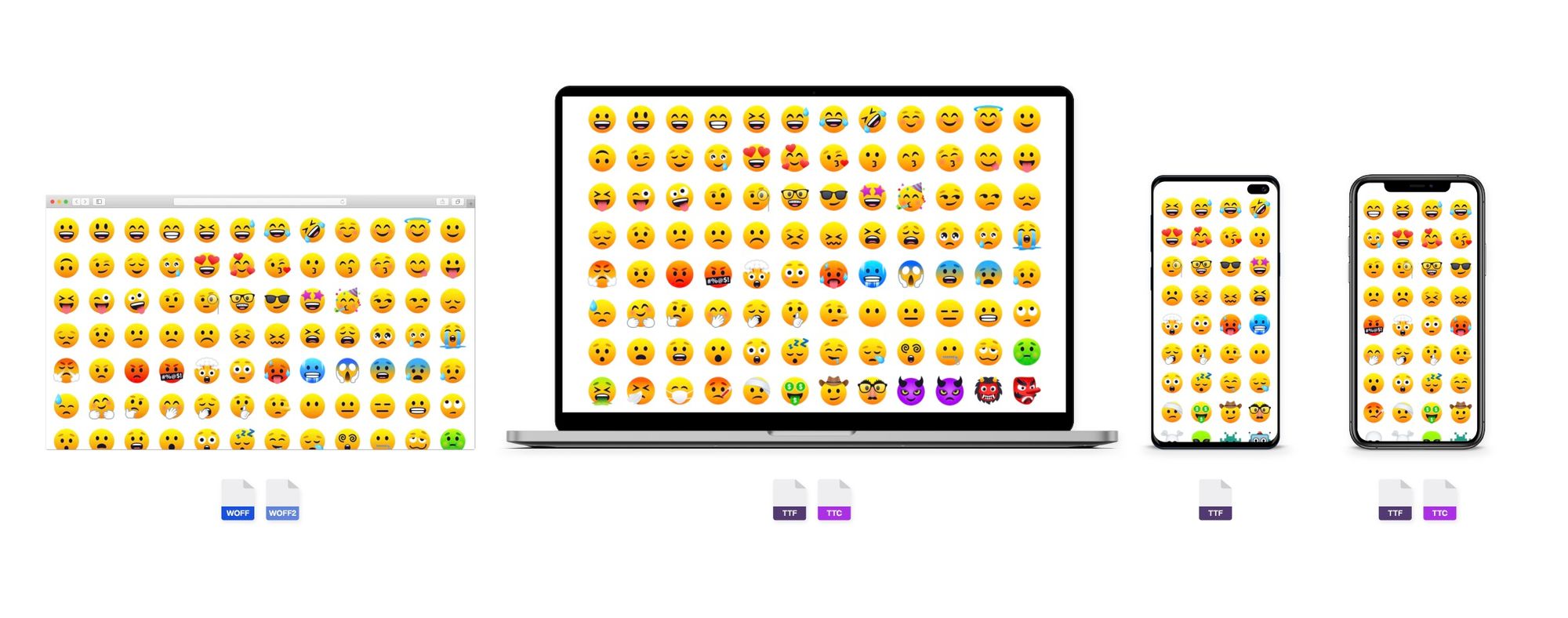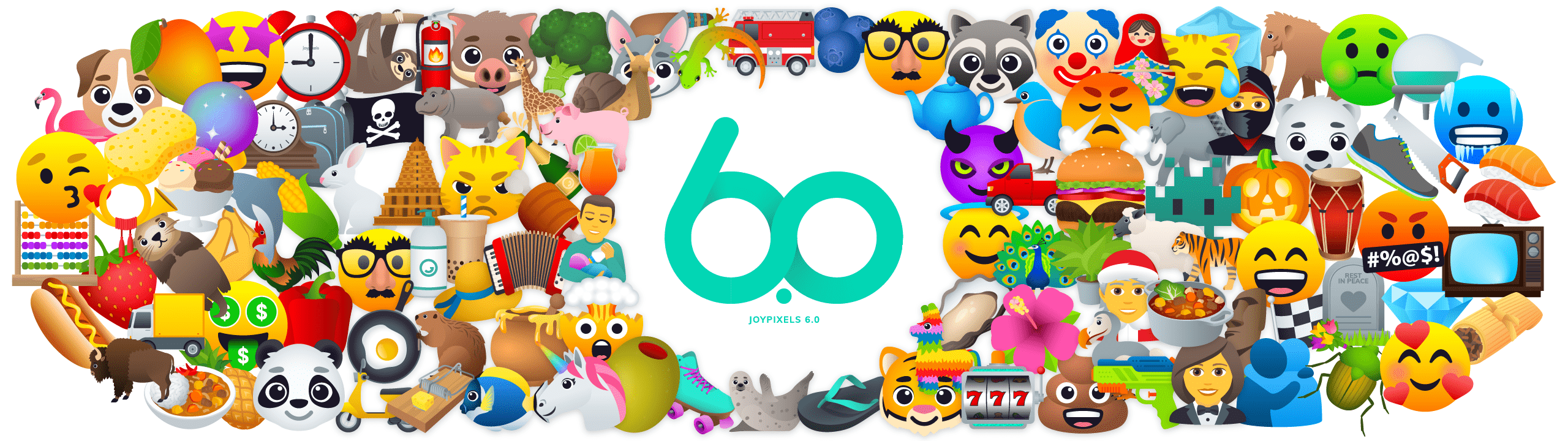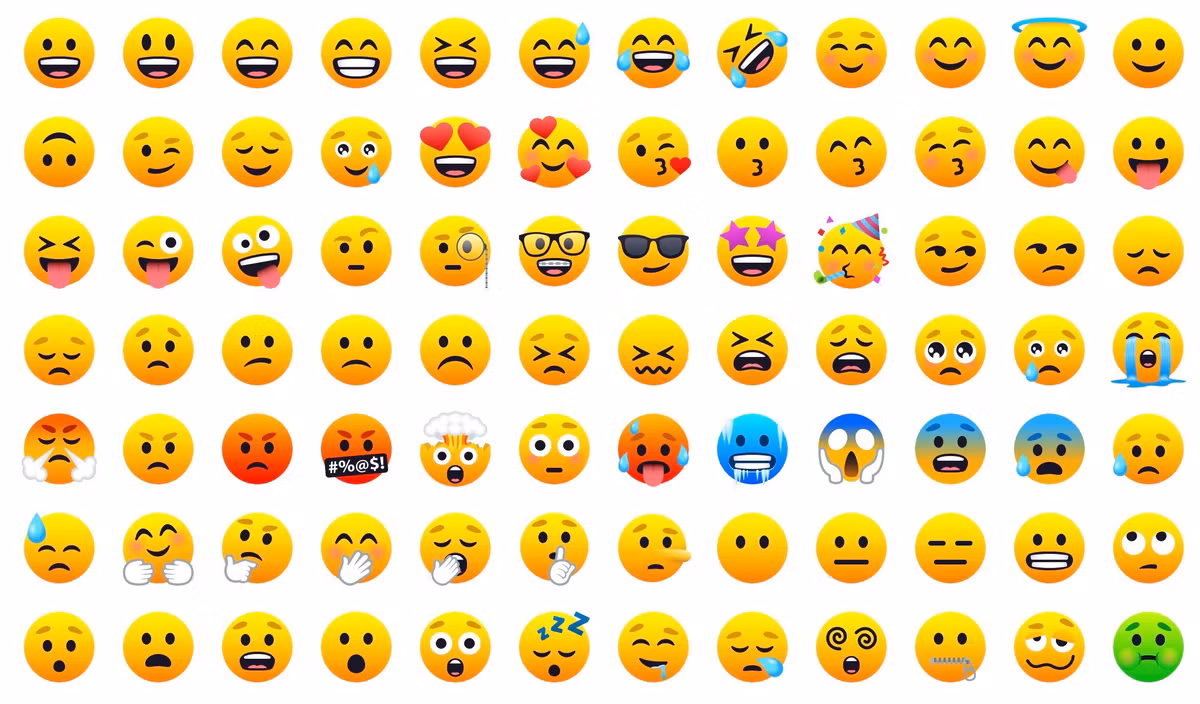
JoyPixels: библиотека эмодзи для коммерческого использования
JoyPixels: библиотека эмодзи для коммерческого использования. Лучшие смайлы, которые вы можете использовать легально.
Лучшие смайлы, которые вы можете использовать легально. Если вы хотите добавить эмодзи на свою веб-страницу или в WordPress, обратитесь к JoyPixels.
JoyPixels был рожден по необходимости и из доброй воли. В сентябре 2014 года основатель Рик Моби выпустил бесплатный набор эмодзи с открытым исходным кодом (EmojiOne), состоящий из около 1000 оригинальных иконок эмодзи. Это был первый в своем роде набор с открытым исходным кодом, который был доступен для простого удовольствия и обмена.
До EmojiOne не было известно о существовании варианта лицензирования полного набора смайликов. Работая с ограниченным бюджетом, качество дизайна было скромным, но эффективным. Успех был мгновенным, и он быстро стал одним из самых распространенных активов на JSDelivr. Революция эмодзи началась.
Перенесемся в 2018 год. JoyPixels (ранее EmojiOne) собирается выпустить 4-е поколение собственных значков смайликов с нашей библиотекой, содержащей более 3000 значков и наклеек смайликов. Это больше не хобби, мы стали ведущим поставщиком смайлов корпоративного уровня. В наш список лицензиатов входят учителя, изобретатели, компании из списка Fortune 500 и тысячи других по всему миру.
«История не показала, что ни один другой поставщик эмодзи не обновлял дизайн так часто, как EmojiOne». -Джереми Бердж (emojipedia.org)
Новое в JoyPixels 5, премиальные шрифты эмодзи состоят из файлов открытого веб-формата шрифтов в форматах PNG и SVG.
Они идеально подходят для веб-проектов, поскольку предоставляют простой способ нормализовать эмодзи, которые испытывают конечные пользователи при посещении вашего сайта.